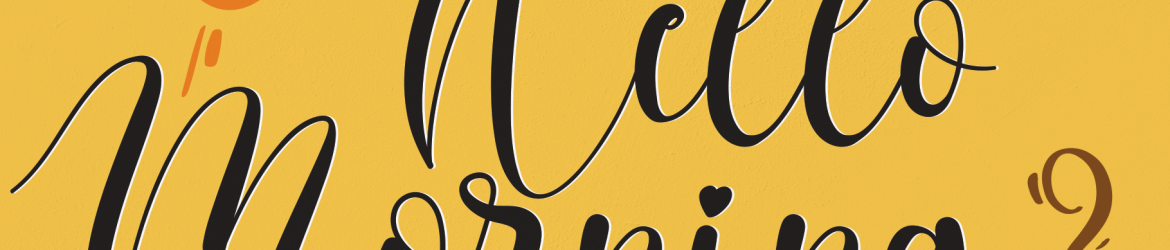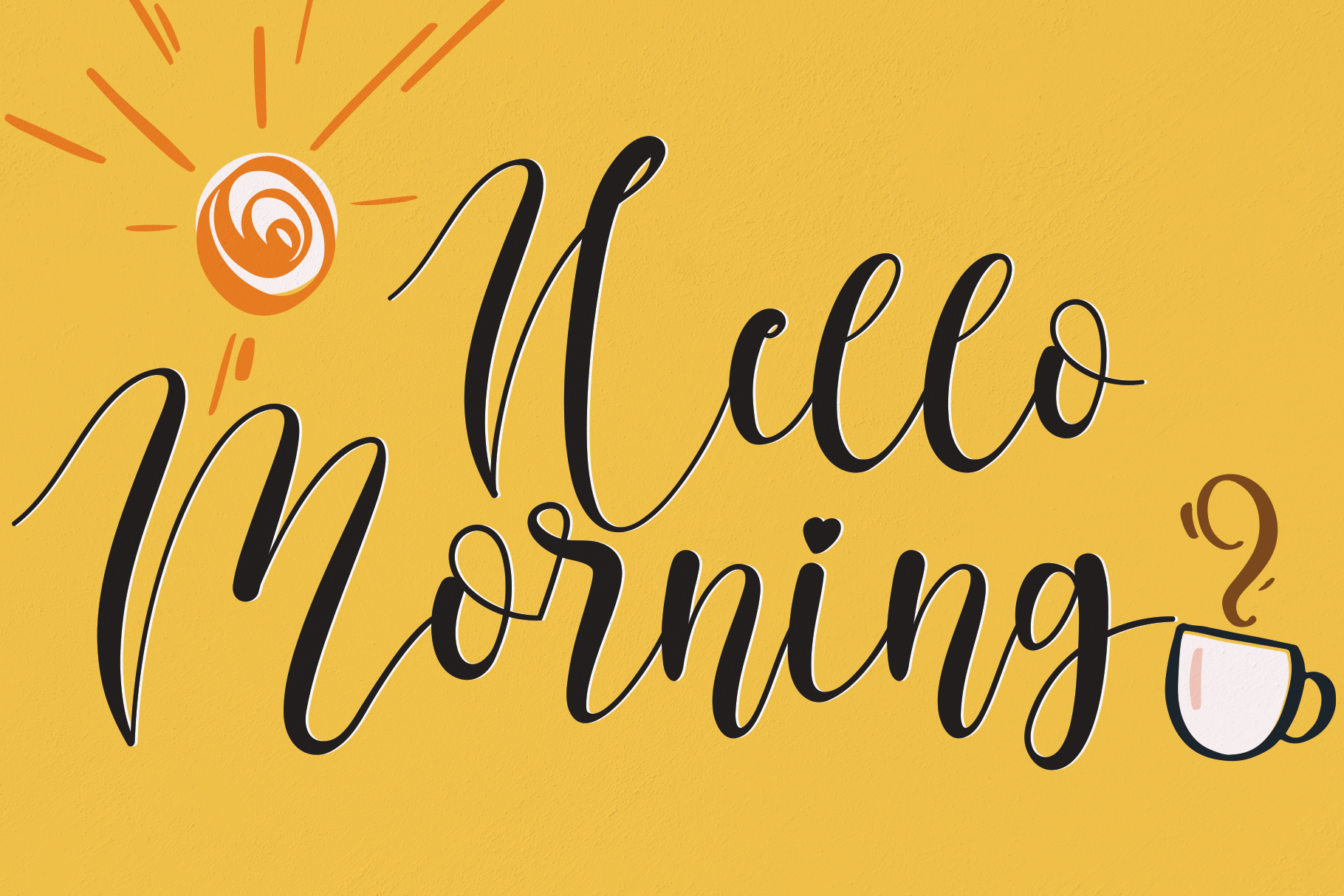
Hello Morning Font
Descubra a beleza da ‘Hello Morning Font’, uma mão-direita que transborda do design elegante e da simplicidade do momento diário. Escolha esta curiosa e única fonte para criar texturas únicas, desde selos até invitations de aniversários. Ela atua perfeitamente para aplicações variadas como postais, embalagens de produtos, etiquetas, logotipos de redes sociais ou até mesmo para as imagens digitais, proporcionando um toque autêntico e original a qualquer projeto que você esteja criando. Composta por letras feitas à mão, a ‘Hello Morning Font’ é uma jóia rara no universo das fontes, perfeita para quem busca unir elegância e simplicidade num só produto. Em sua categoria de Handwritten Fonts, a fonte original ‘Hello Morning Font’, criada pelo designer creativeletter, oferece um toque pessoal em cada projeto que você criar.